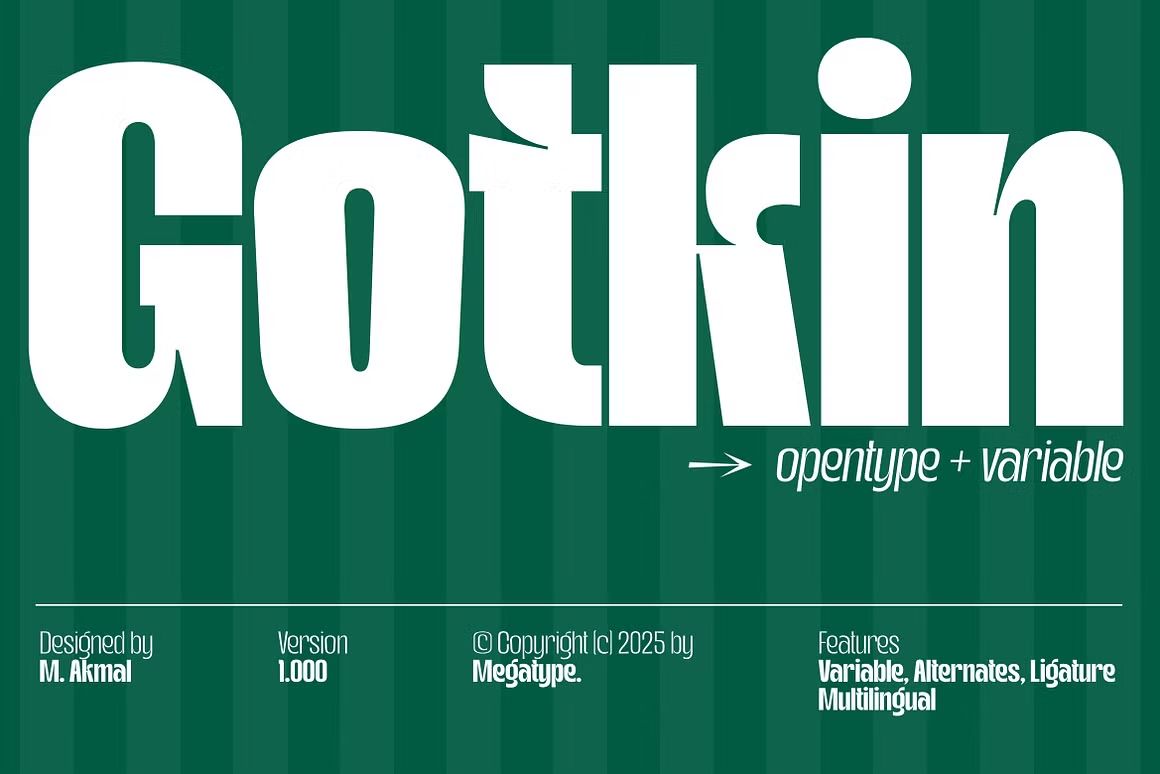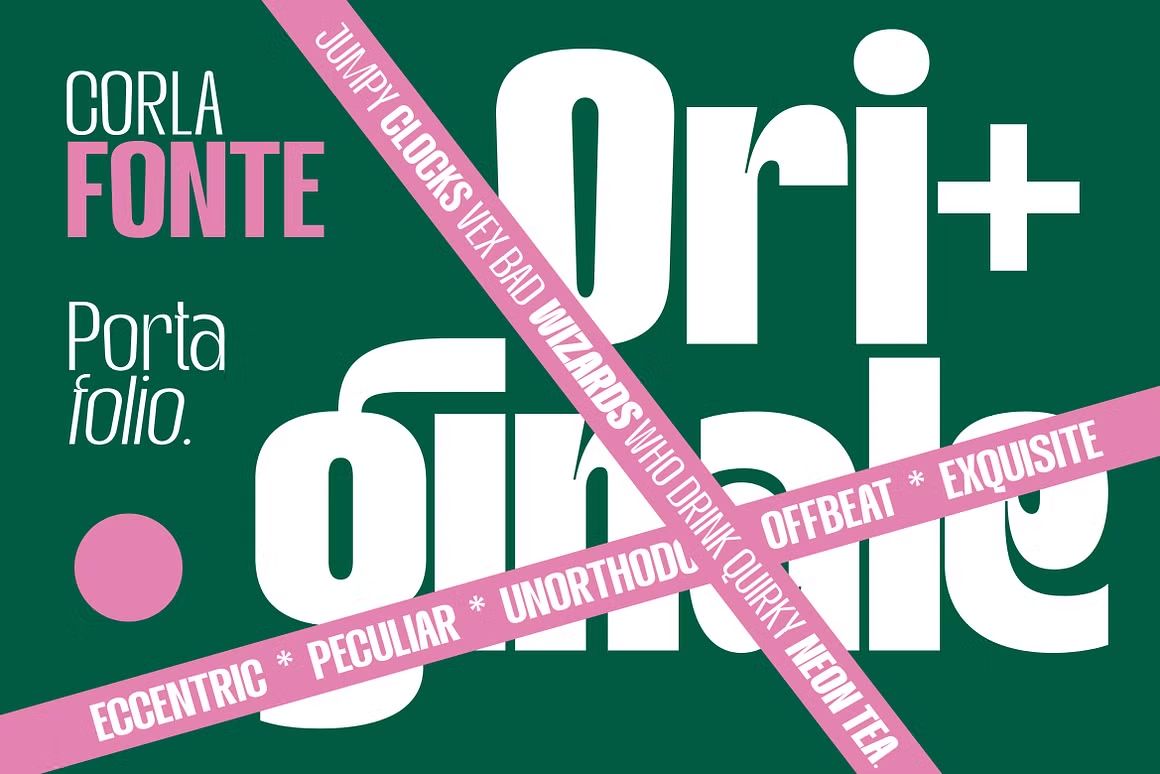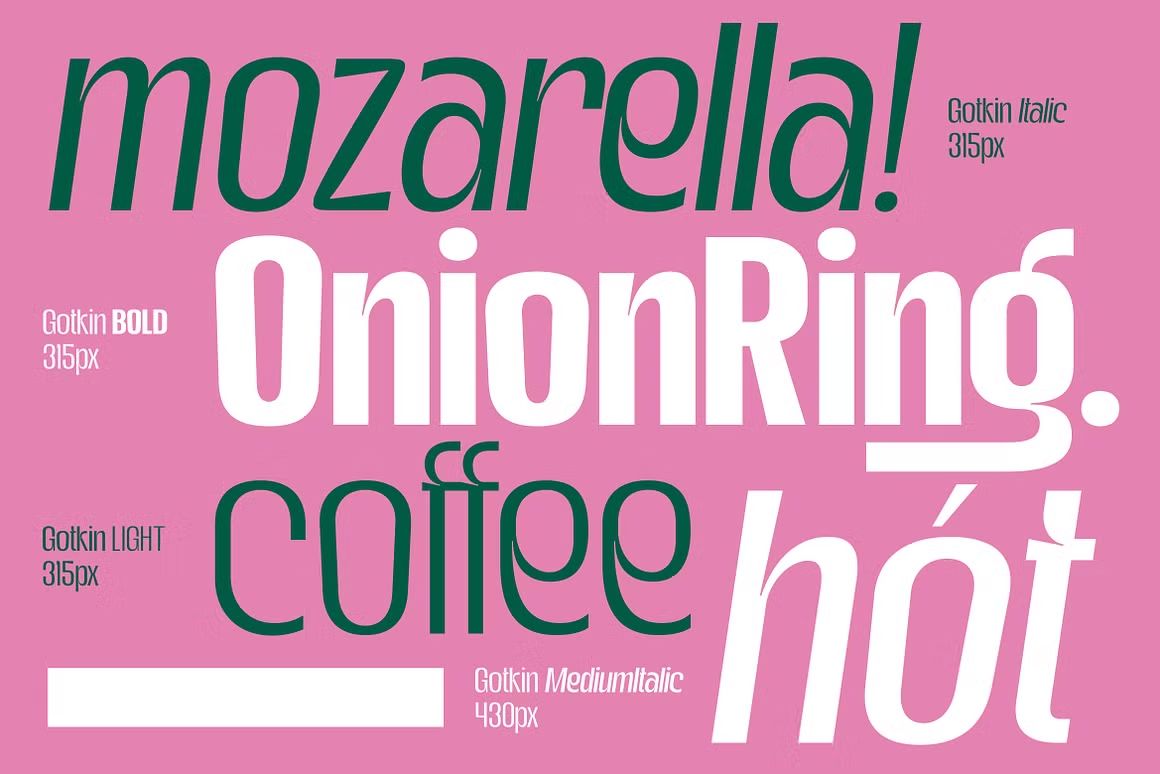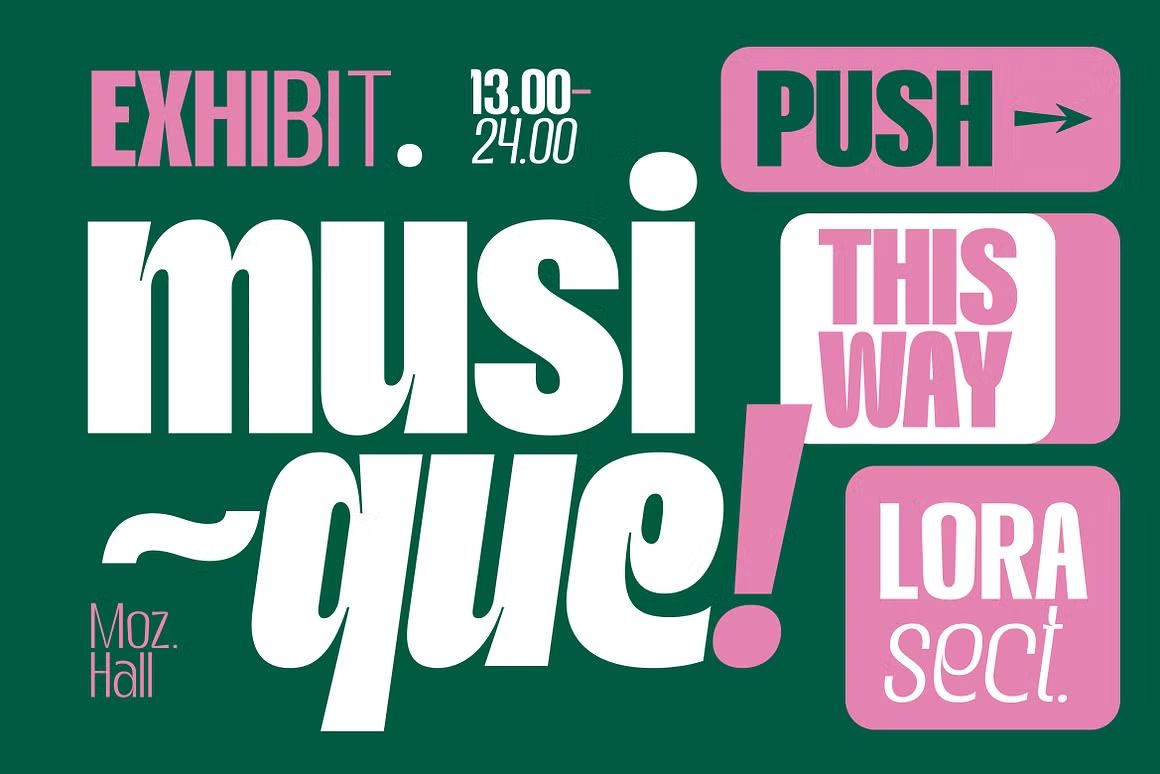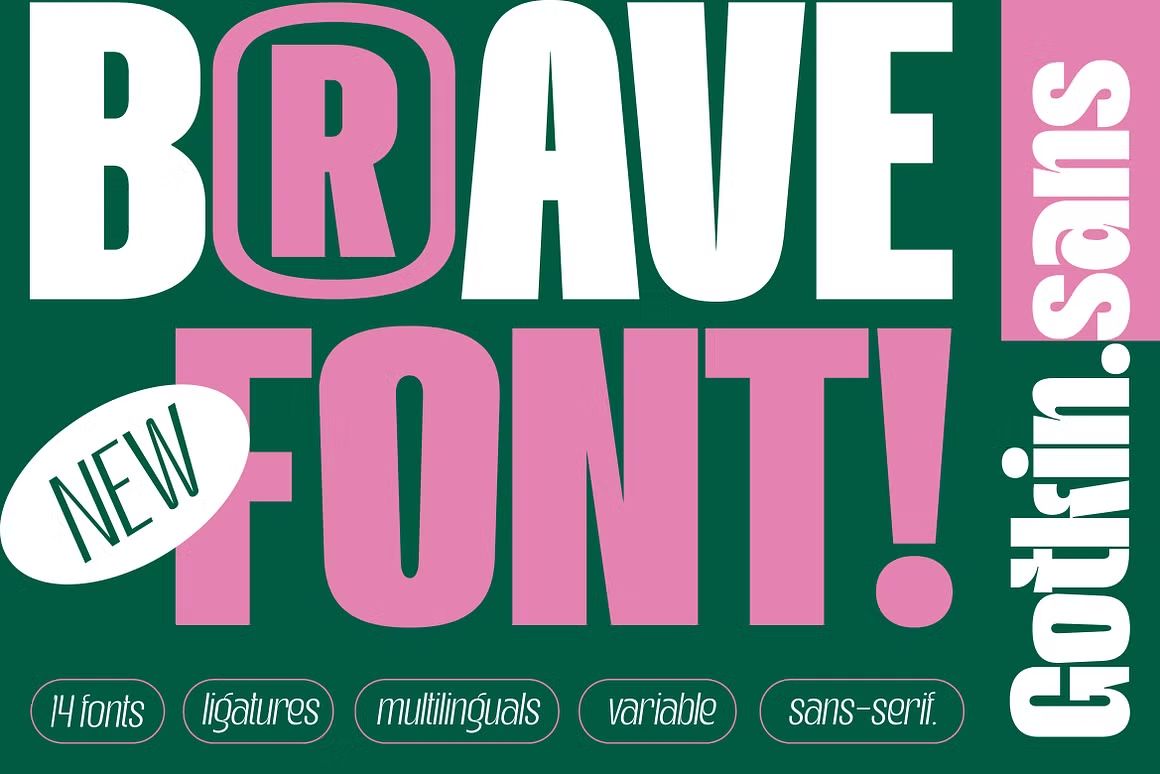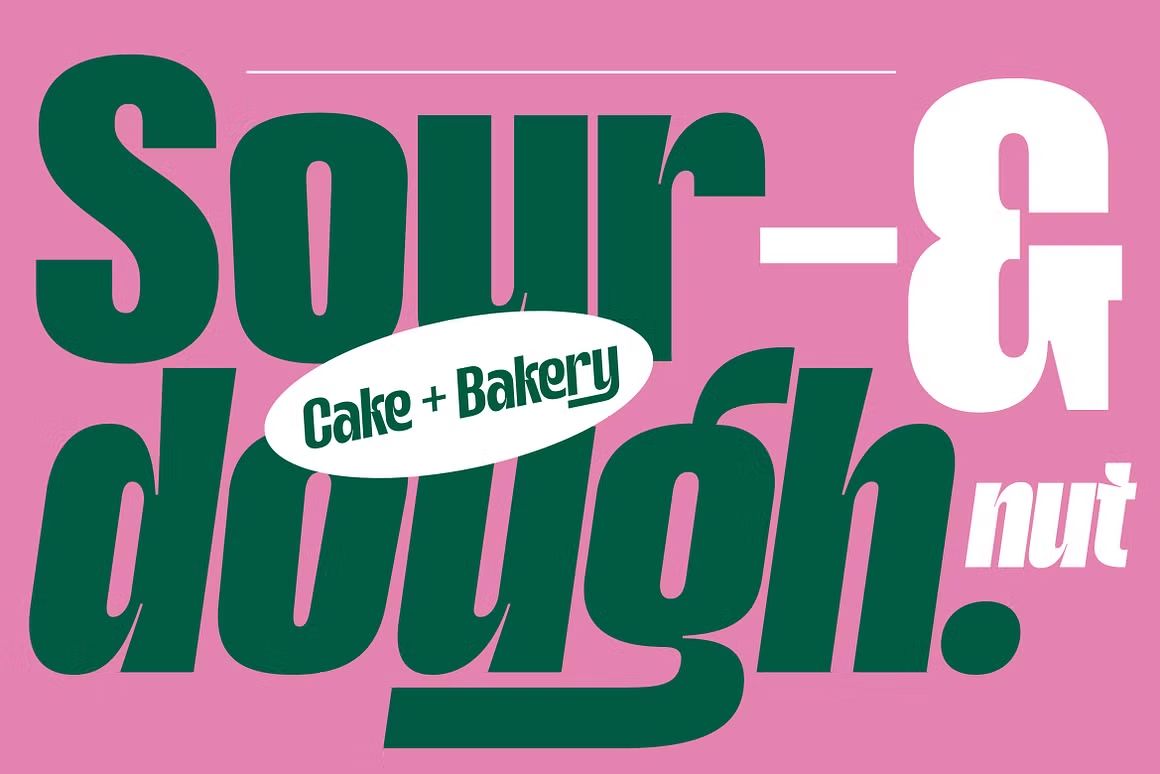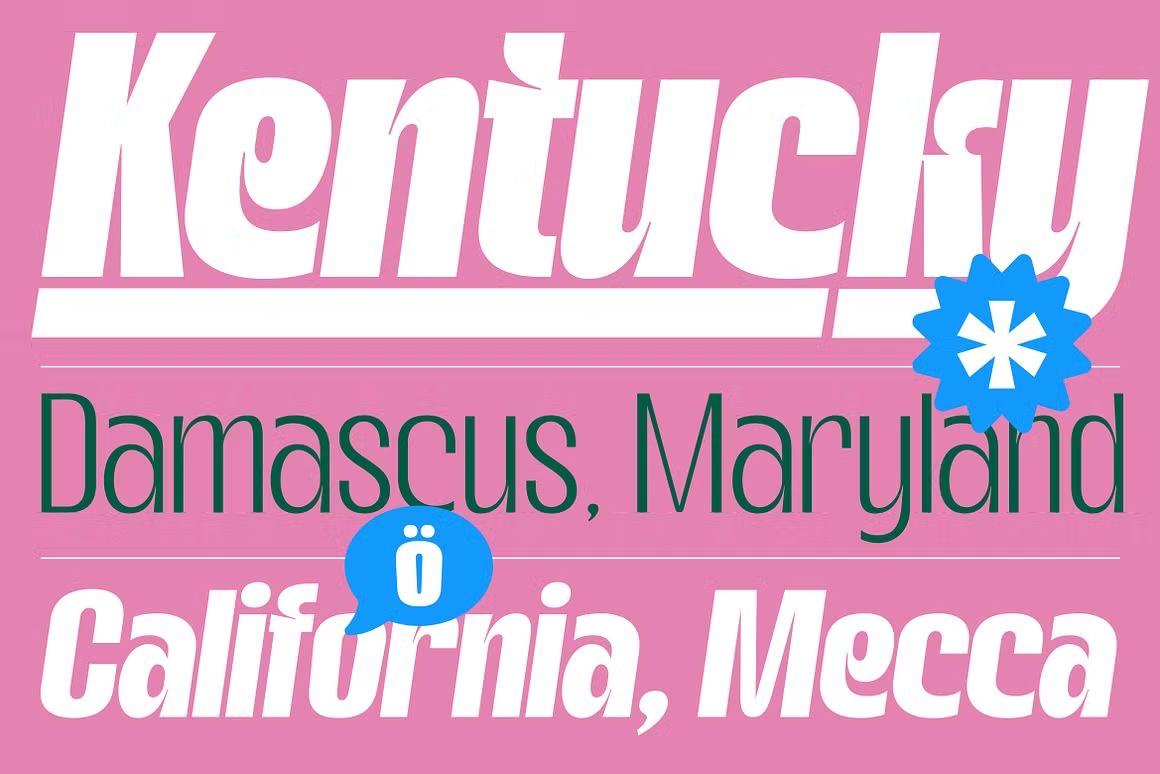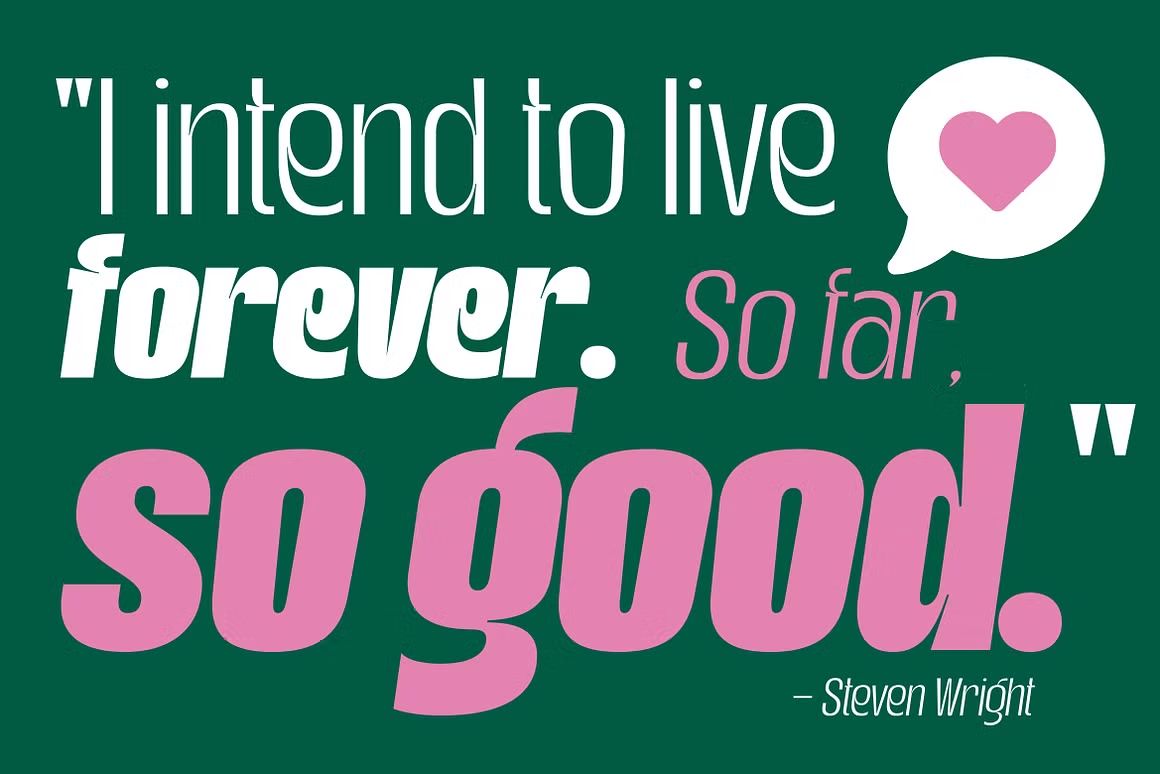
Gotkin – Sans Serif Font
Gotkin adalah font sans serif modern dan minimalis, cocok untuk branding, logo, dan desain profesional. Format OTF/TTF/WOFF, siap digunakan di berbagai platform.
Gotkin adalah font sans serif modern dengan tampilan bersih, minimalis, dan profesional. Didesain dengan proporsi seimbang dan bentuk huruf geometris, Gotkin sangat cocok untuk branding, logo, desain editorial, web design, dan kemasan produk. Font ini menawarkan keterbacaan tinggi serta tampilan elegan yang serbaguna untuk berbagai kebutuhan desain visual.
• Sans serif modern dengan garis bersih dan rapi
• Ideal untuk branding, editorial, dan tampilan digital
• Termasuk huruf kapital, kecil, angka, dan simbol